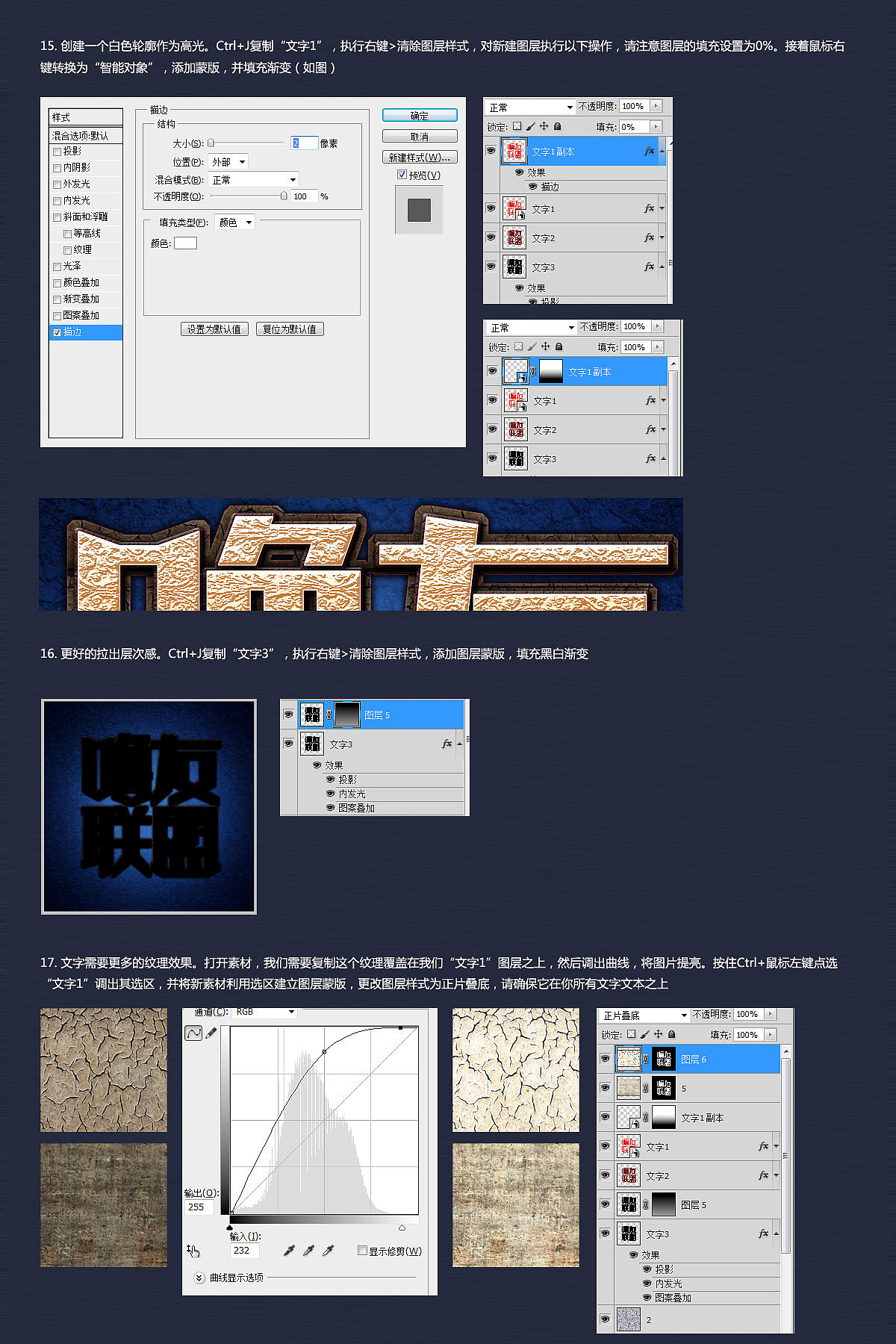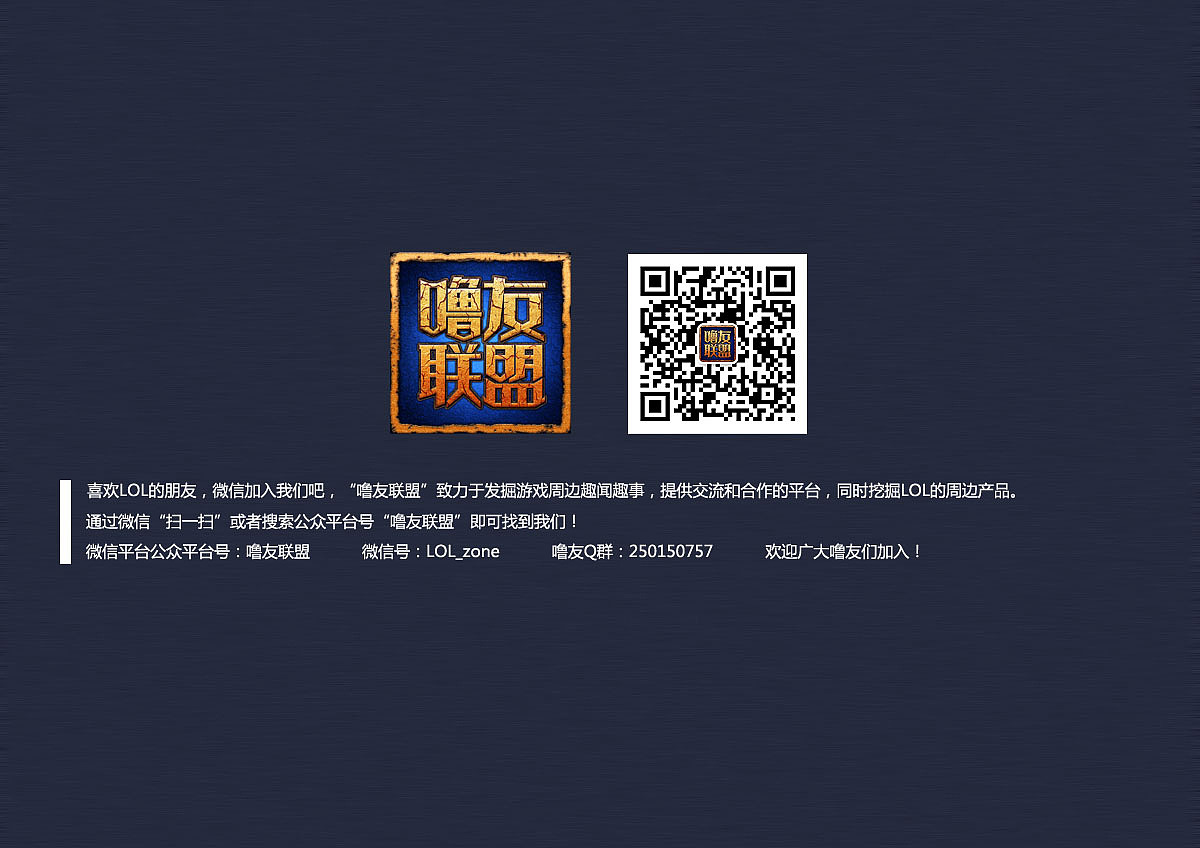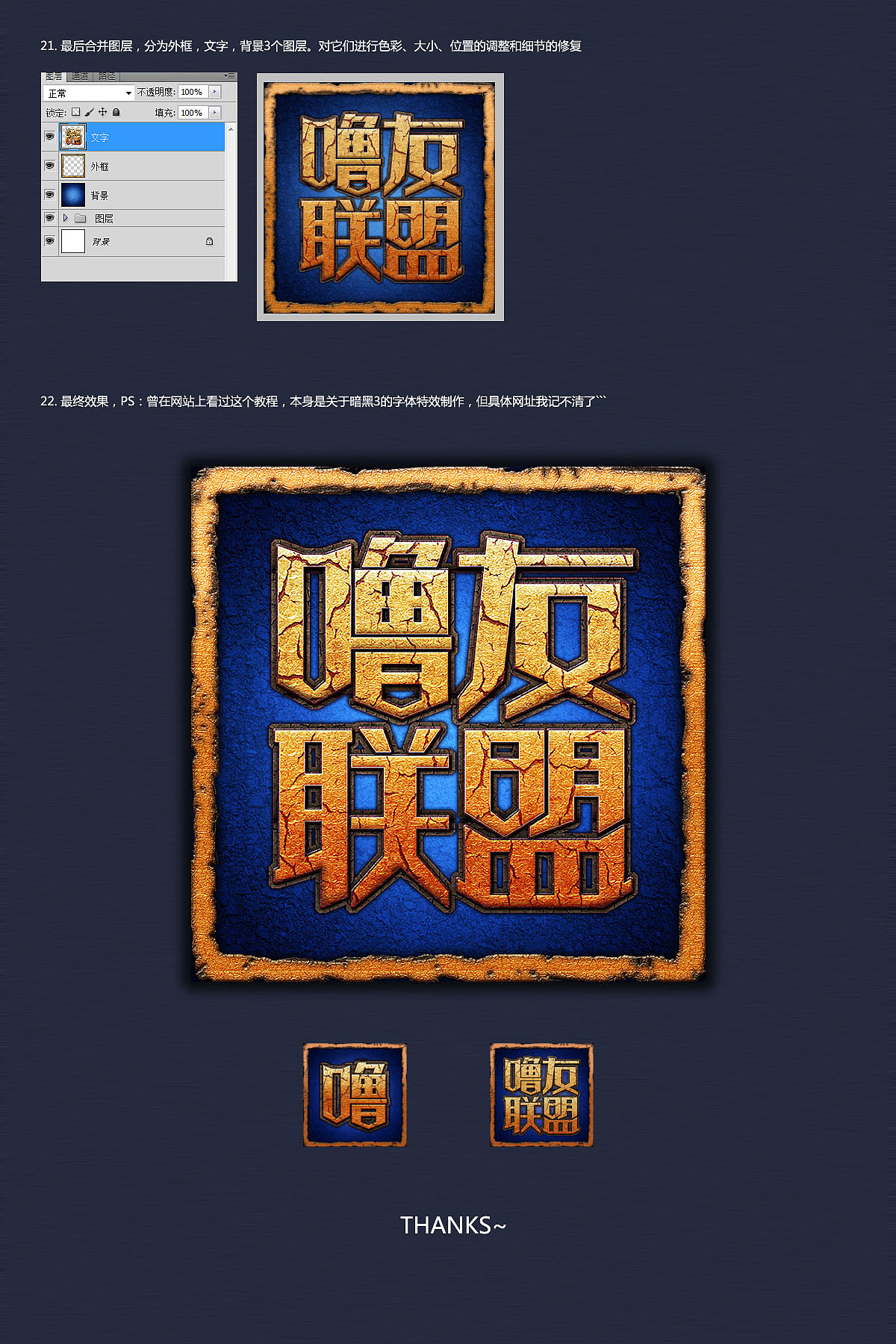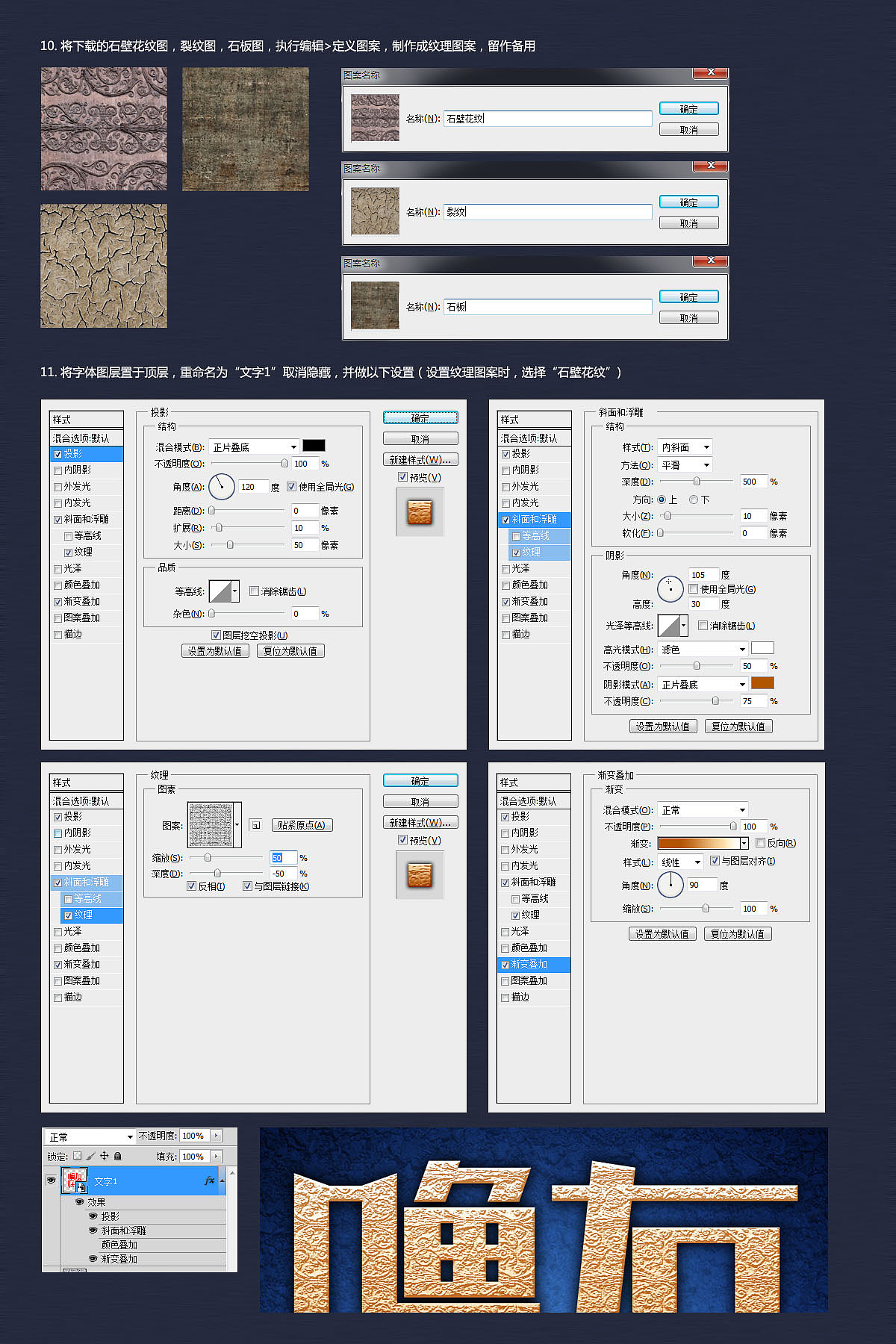
“噜友联盟” 字体设计+图标设计
本人生活之余喜欢玩LOL(英雄联盟),暗影岛、艾欧尼亚、黑玫都有玩,打的都是路人局。不知道站酷的朋友们闲暇之余都有些什么活动,最近申请了个微信公众平台,取名“噜友联盟”想广大噜友齐聚一堂,同时设计了一个图标,仿照LOL的图标风格,希望对LOL感兴趣的朋友们一起加入我们!